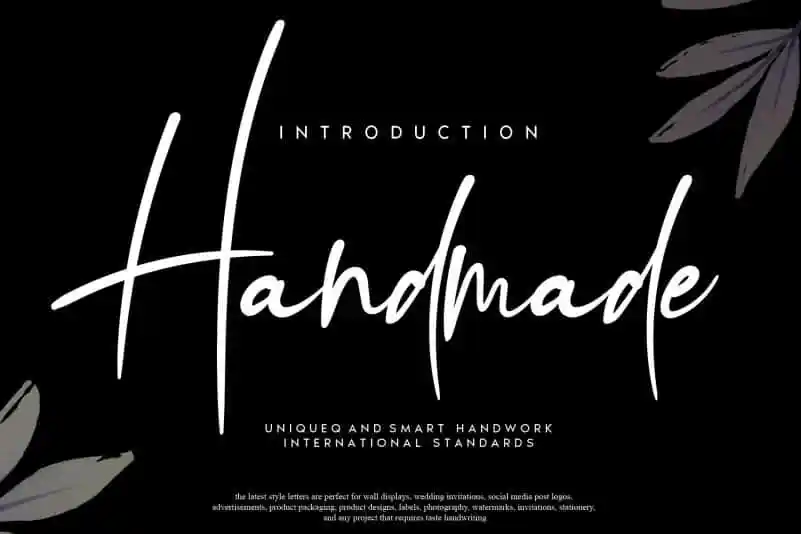
Handmade Script Font – Download Grátis
Descrição para a página de download da fonte Handmade Script Font: Saiam do mundo dos títulos digitais e mergulhem no encanto da autenticidade com a Fonte Handmade Script Font, criada pelo designer andikastudio. Este é um verdadeiro trabalho artesanal, feito à mão para fornecer uma experiência única ao usuá-lo em projetos de texto. Com seu charme natural e seus traços suaves, a Handmade Script se destaca entre as fontes digitais, oferecendo uma textura que flui sem pausa. Ela é perfeita para criar um toque pessoal em websites ou documentos, tornando suas mensagens mais autênticas e emocionantes. Tornar-se esta fonte é como receber um presente do seu designer favorito – algo que se encaixa perfeitamente em seus projetos. Ideal para designers de sites, editoras digitais, e até mesmo criadores de conteúdo que buscam adicionar uma pitada mais pessoal a seus trabalhos. A Handmade Script é a fonte perfeita para os amantes da arte digital, aqueles que desejam imprimir um toque único em suas criações. Não hesite em experimentar, sua experiência no mundo dos projetos digitais certamente será marcada pela presença desta autêntica fonte.